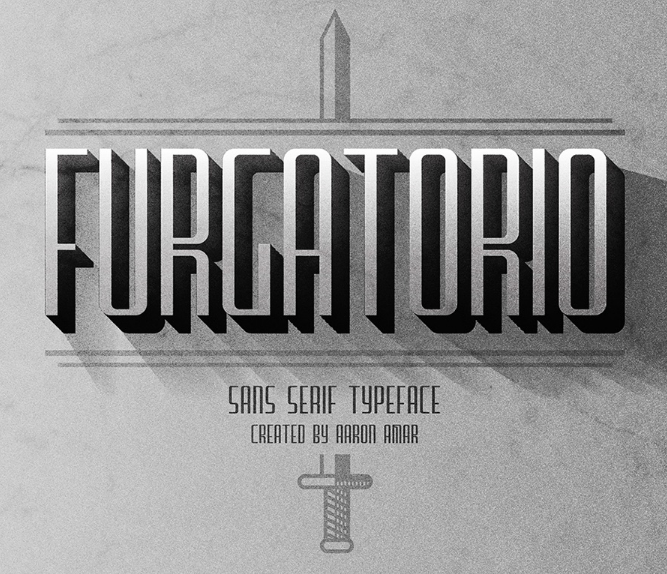
Introduzimos a Furgatorio Sans Família. Esta família foi criada pelo designer Aaron Amar e compartilhada por ele com todo mundo, sendo uma tipografia sans-serif que combina um toque de simplicidade e minimalismo ao mesmo tempo que oferece um design limpo e impressionante. Com dois diferentes níveis de peso, ela é perfeita para layouts de revistas, convites, cabeçalhos ou até mesmo obras de arte em grande escala. O modernismo da Furgatorio Sans se manifesta claramente através do equilíbrio entre largura e altura, especialmente nos caracteres minúsculos. Essa harmonização garante uma legibilidade excepcional, tornando-a uma fonte ideal para uso em qualquer tipo de projeto gráfico que exige uma apresentação moderna e eficaz. Sujeitada a um olhar atento aos detalhes, a Furgatorio Sans é certamente uma escolha inteligente para designers buscando expressar seu trabalho com estilo moderno e alegre.